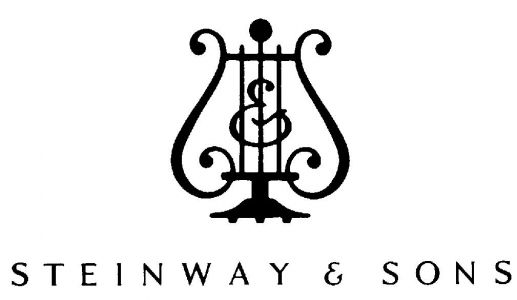
Neue Runde Typo-Quizz gefällig?
und sachdienliche typografische Hinweise:
– der zugehörige Schriftzug hüpft in der DIN-Klassifikation in die Gruppe fünf
– der Slogan ist aus der City von Georg Trump (jedenfalls auf der Webseite)
Na endlich kommen wir der Sache näher.
Ist es das Playboy-Bunnie?
So.
Dieses Mal haben wir es mit einem wunderschönen »S« zu tun.
Ich hoffe, dieses Quiz wird richtig schwer :lol:
Ähm Sisheido nein Schiseido, Sushido, Schubidubidu:
Nein, das stimmt beides nicht.
Und es handelt sich tatsächlich um ein S!
Mhh, wirklich so schwer?!
Kleiner Tip:
Es handelt sich um ein italienisches Traditionsunternehmen mit Sitz in Bologna.
Kaffee?
Das "S" (wenns denn eins ist) schaut zwar nicht so fein aus wie in deinem Beispiel ... aber deren Sitz ist nahe Bologna ... na ja, hätt' ja sein können ...
Nein, auch Segafredo ist es nicht.
Noch ein Tip:
Der Ursprung der herrlichen Jugendstillettern liegt zwar nicht in der Schwarzen Kunst,
hat aber auch etwas mit Farbe zu tun.
Und Gold.
Und es geht weiter:
Leider etwas ausgefranst und klein. Ich habe aber leider keine bessere Vorlage gefunden.
Tipp: Nichts für Jedermann; und teurer als Omas-Füllfederhalter.
Stimmt. Uff. Hätte gedacht das wäre schwieriger. Ich hatte mir auch schon ein paar schöne Tipps ausgedacht ... passt nicht in eine Sozialwohnung u.s.w. ;-)
Mein Lieblingspiano ist eigentlich auch das Bösendorfer, allerdings fand ich kein passendes Logo im Internet. Und den eigenen Flügel mal eben so unter den Scanner legen ist schon etwas problematisch ...
… ist natürlich geschwindelt. Einen Bösendorfer hätte ich nur unheimlich gern ... aber der passt – wie angedeutet – leider noch nicht enmal in meine Wohnung. :oops:
„hey”, du bist dran.
Und den eigenen Flügel mal eben so unter den Scanner legen ist schon etwas problematisch ...
Dann leg’ doch den Scanner auf den Flügel! :wink:
Uh, wie gruselig:
:)
»Model 170« ist doch extra für kleineren Wohnraum ausgelegt! Das wird sich doch wohl machen lassen? Zwischen Waschmaschine und Abfalleimer? :twisted:
Würd' auch gerne mal drauf spielen ...
Damit Ihr mit Euren Kühlschrankflügeln ähh, Waschmaschinen-Flügeln auch was ordentliches anfangen könnt:
Mal zwischendurch ne andere Art von Rätsel :wink:
Wer hat’s? Immer noch kein Anrufer in der Leitung? Leute, jetzt müßt ihr Gas geben! Das kann doch nicht sein! Niemand, der das weiß? (etc.)
Wenn der „typografische Fachbegriff“ wirklich „MAC“ lauten sollte... dann... hat die Marketing-Abteilung dieser Firma ja wohl ganze Arbeit geleistet über die Jahre... Sagt denen vielleicht mal jemand, dass „MAC“ nicht gebrüllt gehört, sondern klein geschrieben wird? Eine Frage der Maciquette...
Sondern? „_ _ _ MMAACC _ _ _“ ergibt doch sonst kein sinnvolles Wort oder gar einen Terminus, oder?
:?: :?: :?:
Lars
Oh, Mann...
Es geht doch bei diesen Sendern überhaupt nicht um Sinn oder Unsinn.
Es geht nur darum, daß die Leute anrufen.
Es ist also müßig, darüber nachzudenken.
Das hat der Jens doch bestimmt in Photoshop gebastelt. Als ob die »Redakteure« bei diesem Sender auf solche Fragen kommen würden ...
Aber die haben doch auch €uros... Die müssen sich ja auskennen.
Das hat der Jens doch bestimmt in Photoshop gebastelt.
Ganz richtig. Ihr braucht mich also nicht anzurufen, dafür hab ich allerdings auch keine 2100 Euro zu verschenken :)
Noch ein Tip zum Rätsel: Man braucht es, wenn man rumänisch schreibt.